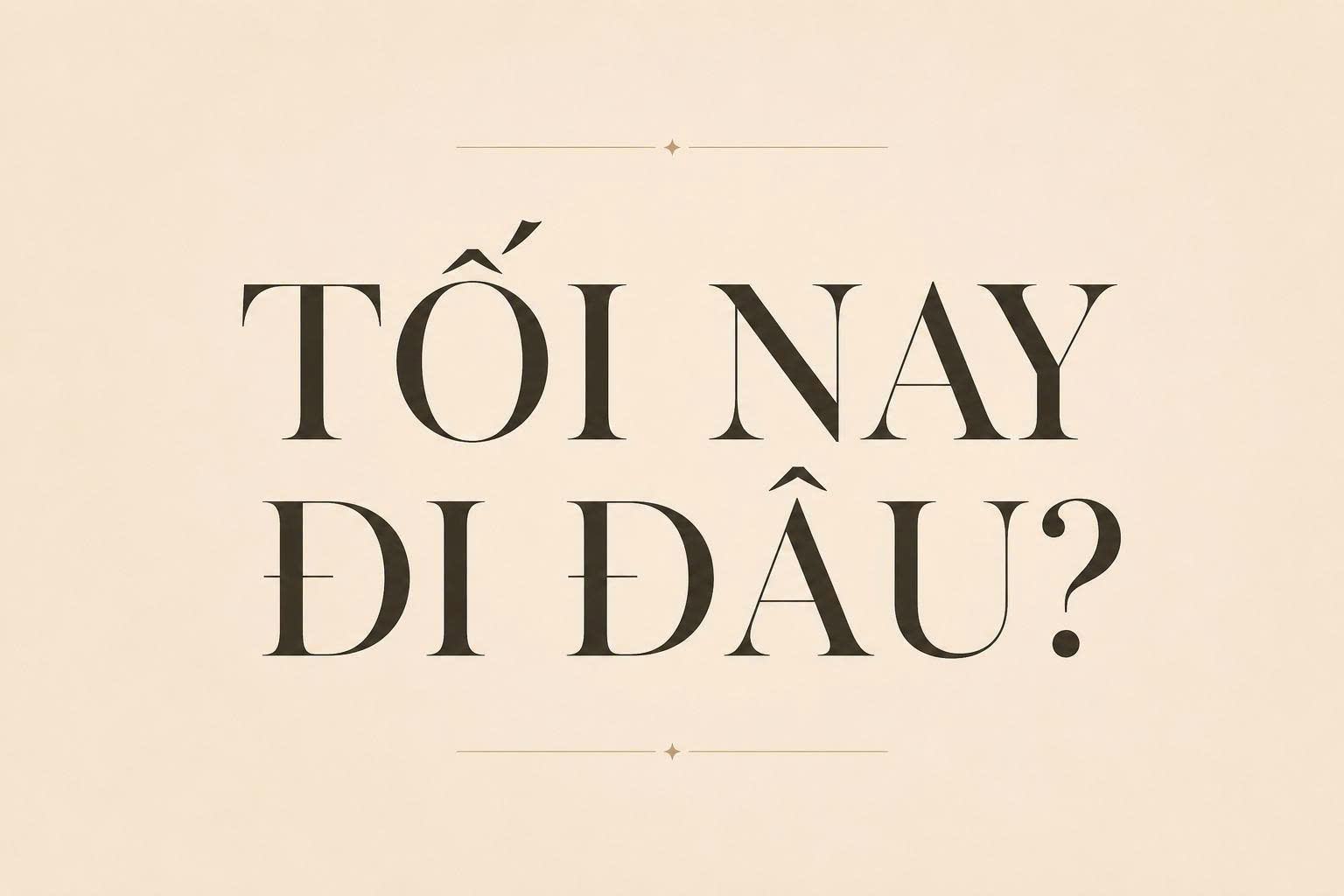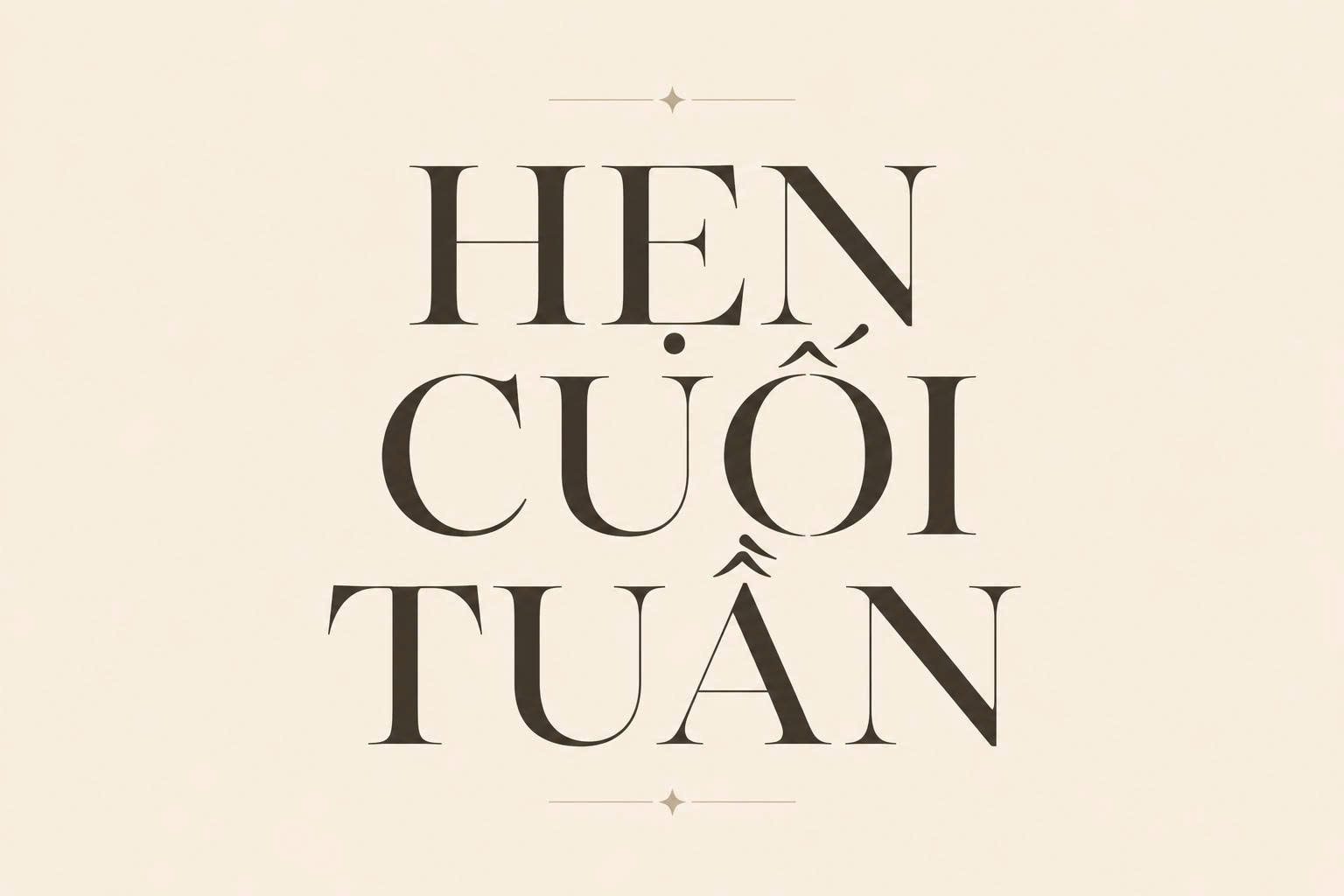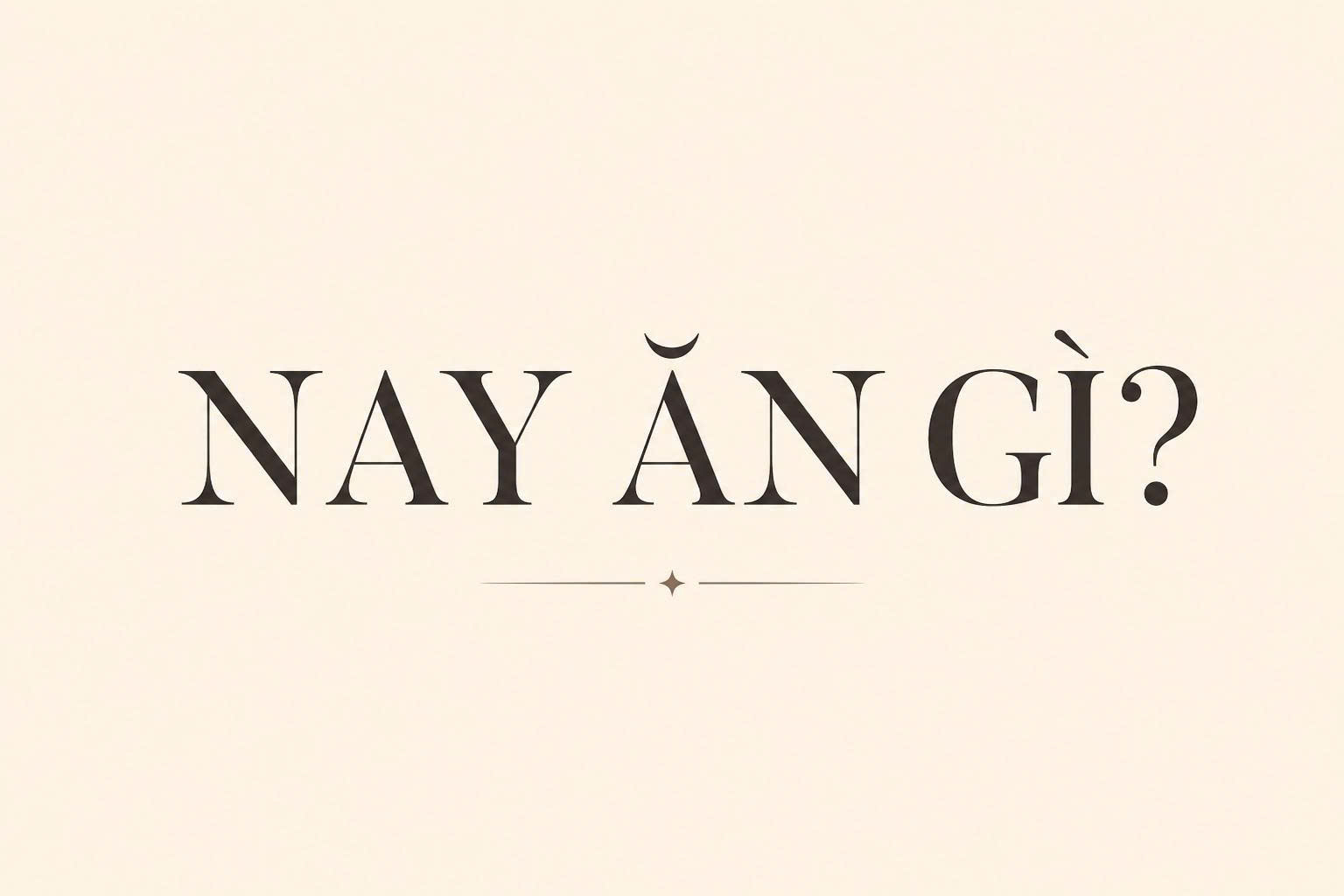
Font Butler Việt hóa là bộ phông chữ có chân (Serif) hiện đại, được thiết kế bởi Fabian De Smet lấy cảm hứng từ hai dòng phông chữ kinh điển Dala Floda và Bodoni. Với sự kết hợp hoàn hảo giữa những đường cong mềm mại và các nét gạch chân sắc sảo, Butler mang lại vẻ đẹp đẳng cấp, sang trọng và vô cùng thời thượng cho các dự án nhận diện thương hiệu. Doozypack.vn cung cấp link tải font Butler Việt hóa trọn bộ, hỗ trợ đầy đủ tiếng Việt giúp bạn tự tin thiết kế bao bì cao cấp, bìa sách nghệ thuật hoặc các ấn phẩm truyền thông mà không lo lỗi font.
Đặc điểm thiết kế tinh tế của bộ font Butler Việt hóa
Butler không chỉ là một phông chữ có chân thông thường; nó là sự tái định nghĩa phong cách Serif truyền thống để phù hợp với ngôn ngữ thiết kế đương đại.
Sự kết hợp hoàn hảo giữa cổ điển và hiện đại
Đặc trưng lớn nhất của font Butler tiếng Việt là độ tương phản nét thanh đậm rất cao, gợi nhắc đến phong cách Didone quý tộc nhưng các đường nét đã được tinh giản để trở nên gọn gàng và tinh tế hơn. Các góc chữ được bo tròn nhẹ nhàng tạo nên sự uyển chuyển, giúp khối văn bản vừa mang tính thẩm mỹ cao, vừa duy trì được sự minh bạch, dễ đọc.
Hệ thống biến thể đa dạng với 14 kiểu chữ
Bộ font Butler bao gồm 7 độ dày khác nhau (từ Ultra Light đến Black) và đặc biệt là phiên bản **Stencil** dành riêng cho các tiêu đề nghệ thuật. Sự phong phú này cho phép designer linh hoạt trong việc phân cấp thông tin (Typography Hierarchy) trên bao bì, từ tên thương hiệu chính cần sự mạnh mẽ đến các thông tin mô tả cần sự thanh lịch.
Tại sao designer nên ưu tiên font Butler tiếng Việt cho bao bì cao cấp?
- Hoàn thiện bộ dấu tiếng Việt: Bản Việt hóa chuẩn đảm bảo các dấu thanh được đặt ở vị trí cân đối, không làm thay đổi chiều cao dòng chữ, giữ nguyên cấu trúc tinh xảo của font gốc.
- Nâng tầm giá trị sản phẩm: Butler mang lại diện mạo “đắt tiền” cho vỏ hộp, phù hợp với các tiêu chuẩn thẩm mỹ của ngành hàng thời trang, nước hoa và mỹ phẩm luxury.
- Tối ưu cho cả màn hình và in ấn: Cấu trúc chữ của Butler hoạt động cực kỳ ổn định, đảm bảo độ sắc nét từ giao diện website đến khi xuất hiện trên chất liệu giấy thực tế.
| Biến thể Font | Đặc điểm thị giác | Mục đích sử dụng đề xuất tại Doozypack.vn |
| Butler Light/Medium | Thanh mảnh, tinh tế | Dùng cho nội dung mô tả, địa chỉ hoặc bảng thành phần trên vỏ hộp. |
| Butler Bold/Black | Vững chãi, quyền lực | Dùng làm tiêu đề chính, tên sản phẩm trên túi giấy hoặc hộp quà. |
| Butler Stencil | Nghệ thuật, phá cách | Dùng cho logo hoặc các điểm nhấn trang trí độc đáo trên bao bì. |